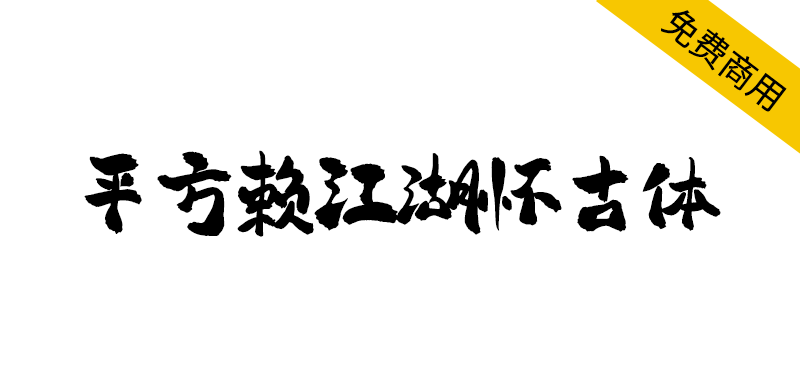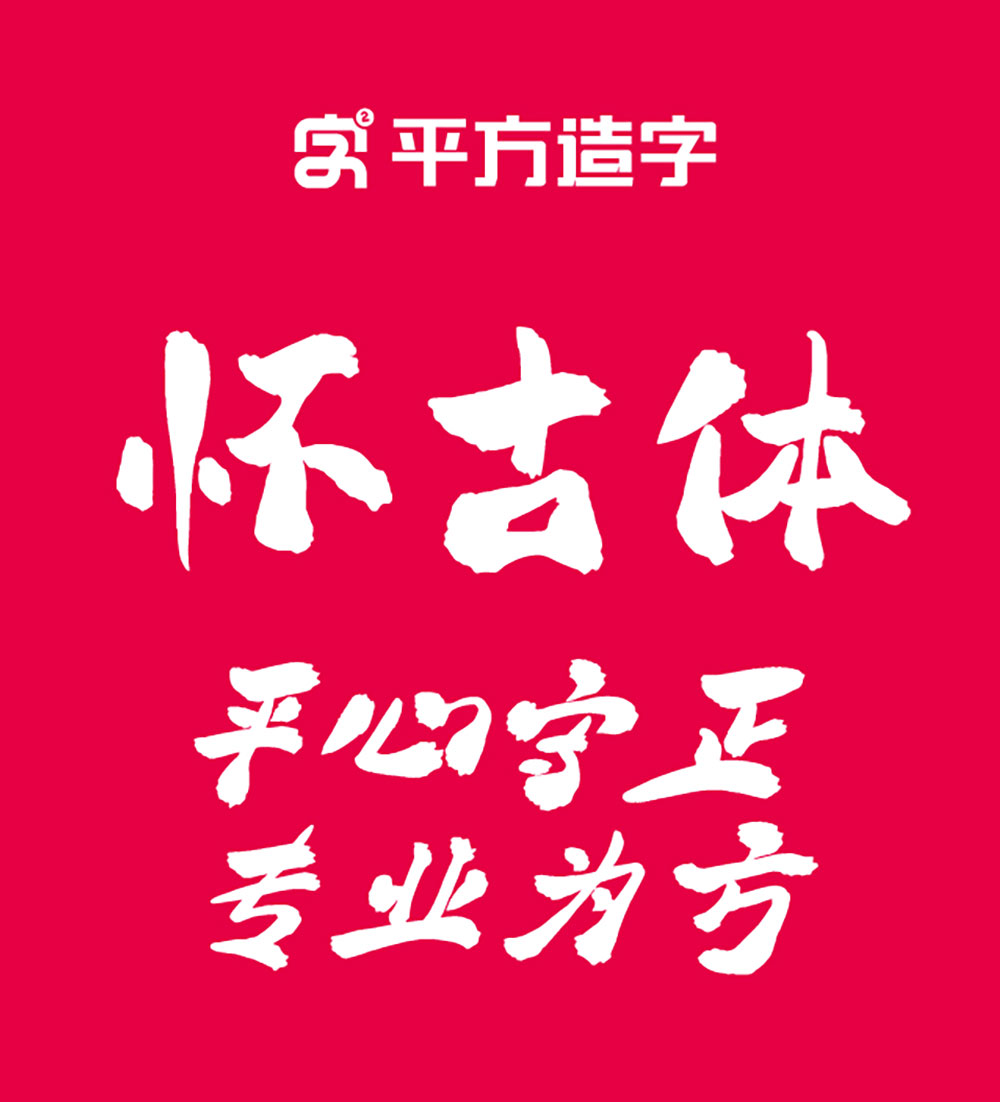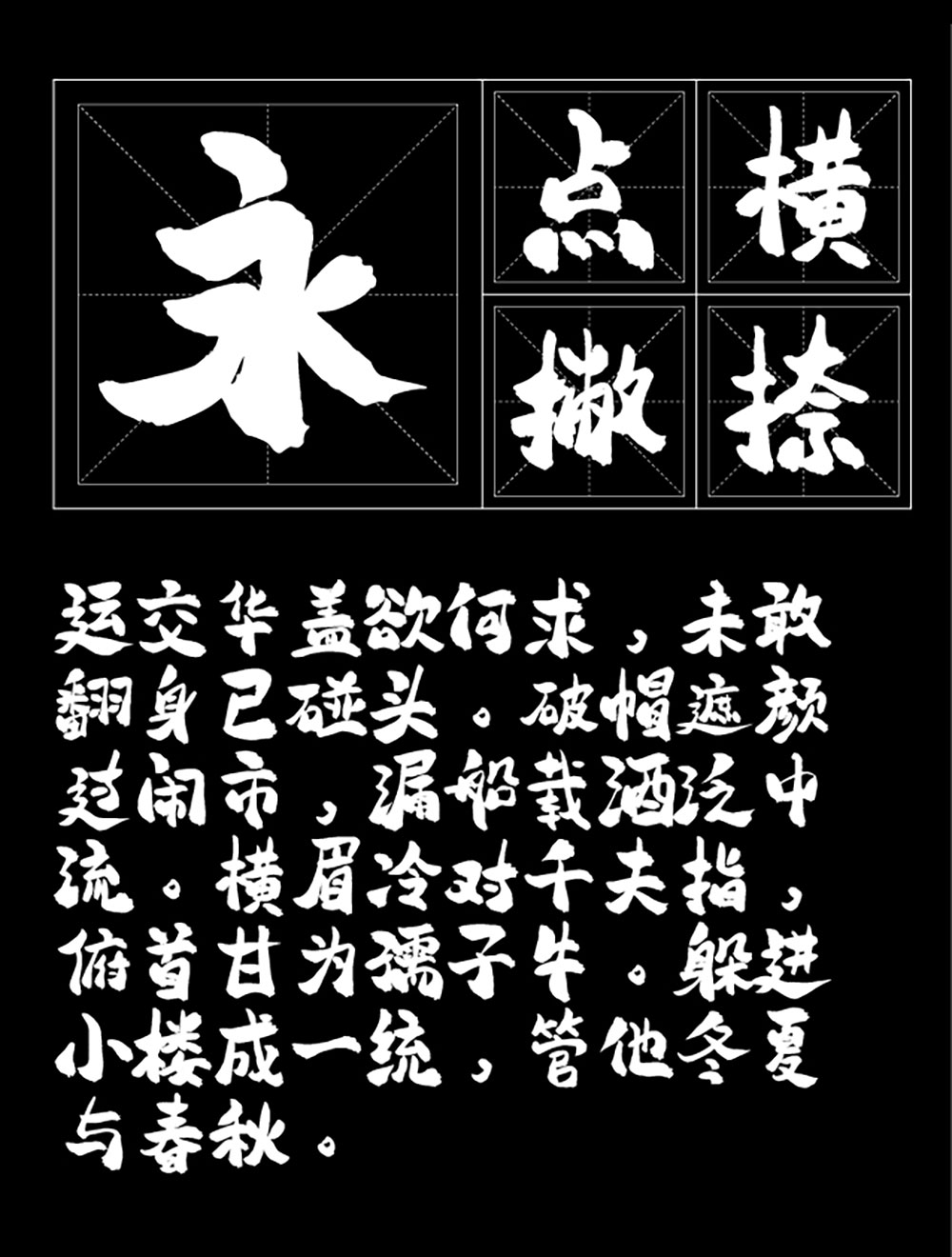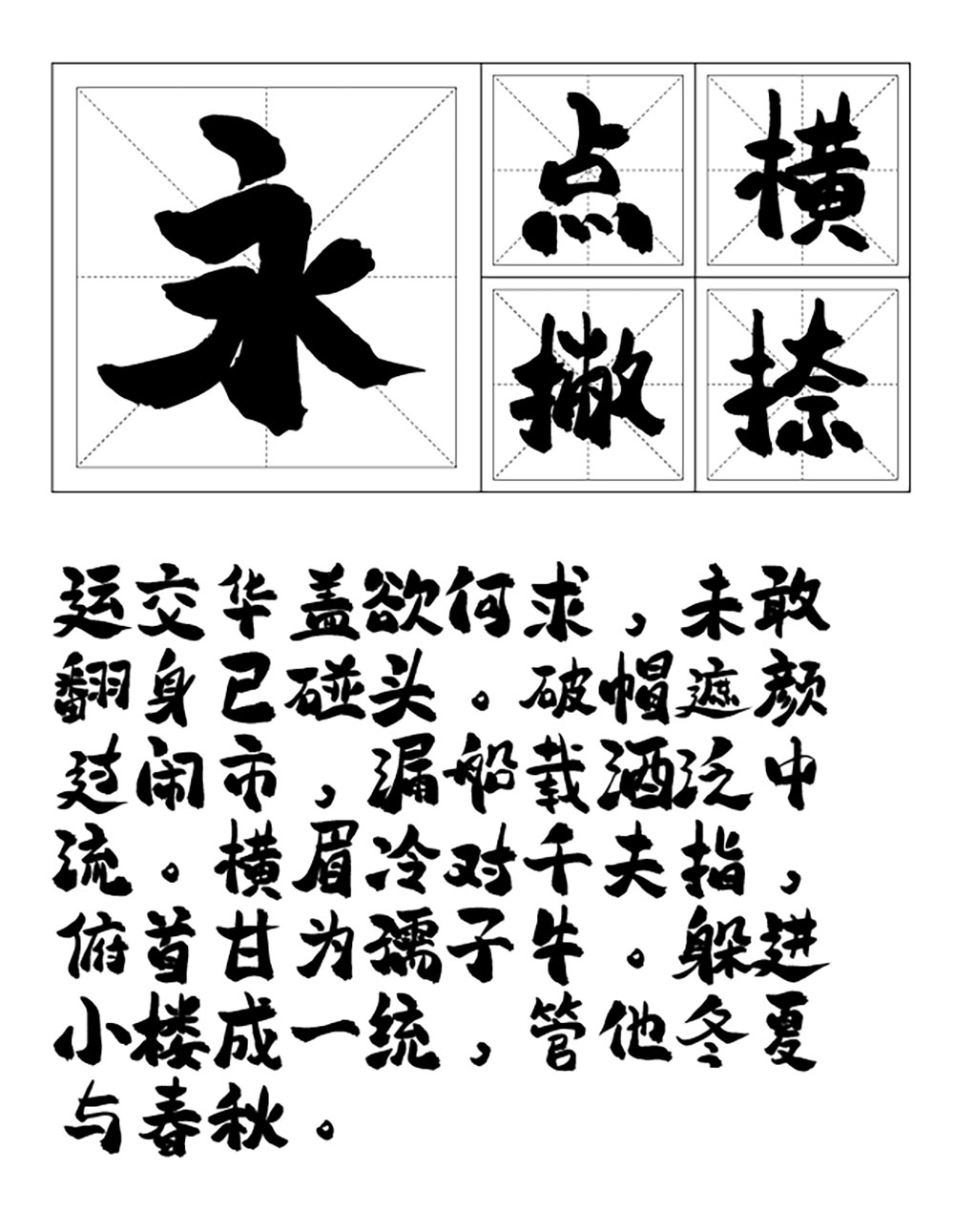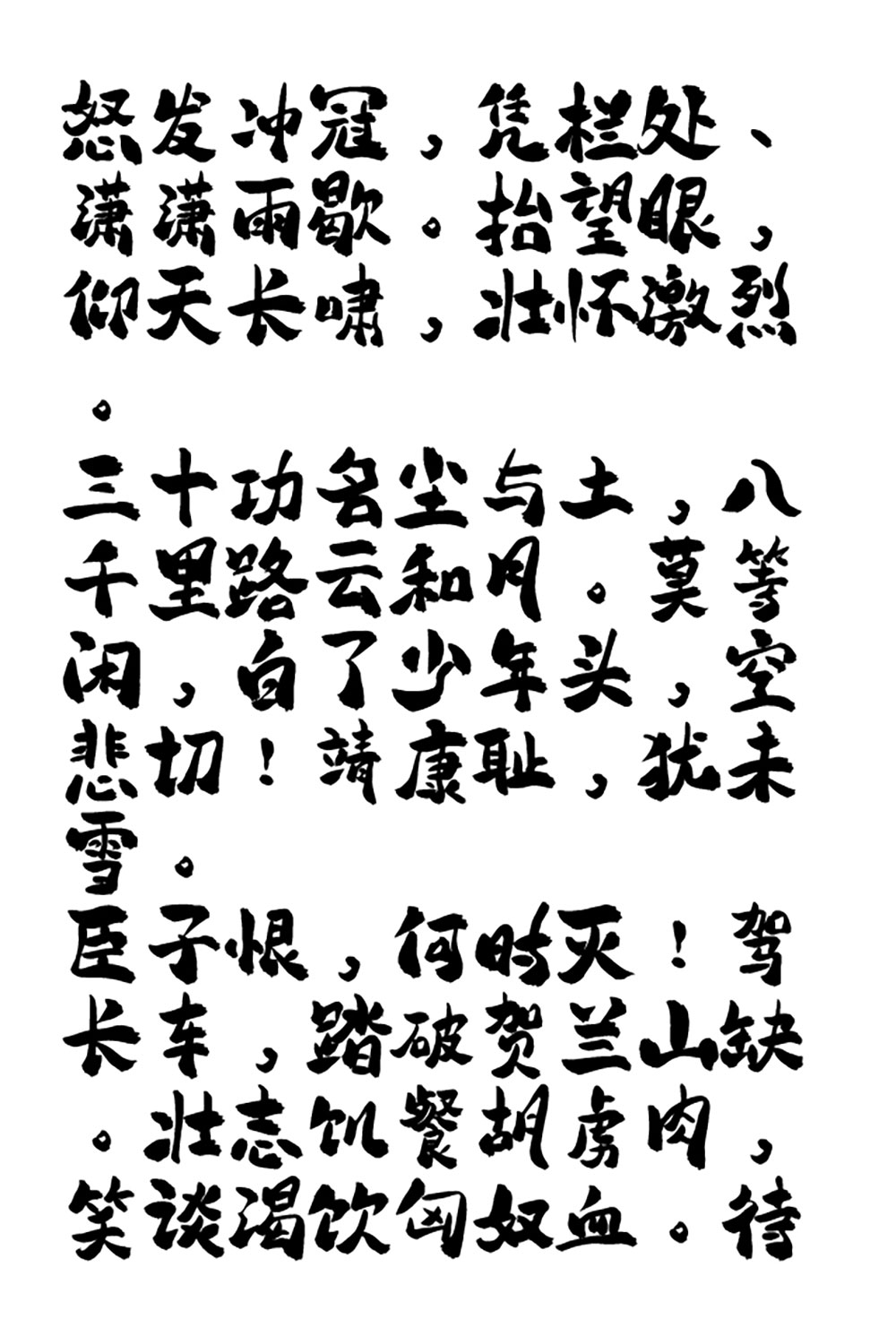
【平方赖江湖怀古体】一款具有传统书法韵味的毛笔书法字体
寻找一款既能彰显文化底蕴又适合商业使用的字体?平方赖江湖怀古体,这款毛笔手写字体以浑厚饱满的笔触和刚健有力的风格,完美诠释江湖古风。书法名家赖江湖倾心创作,收录6763汉字,更难得的是允许个人和企业免费商用。它不仅是一件艺术品,更是提升设计品质的实用利器。
【平方赖江湖怀古体】一款具有传统书法韵味的毛笔书法字体
平方赖江湖怀古体是一款具有传统书法韵味的毛笔手写字体,其设计灵感源自毛笔书法艺术,具有江湖、古风气息。该字体笔触特征鲜明,起笔与收笔处线条浑厚饱满,整体笔画刚健有力,呈现出协调统一的书写风格。
【平方赖江湖怀古体】一款具有传统书法韵味的毛笔书法字体